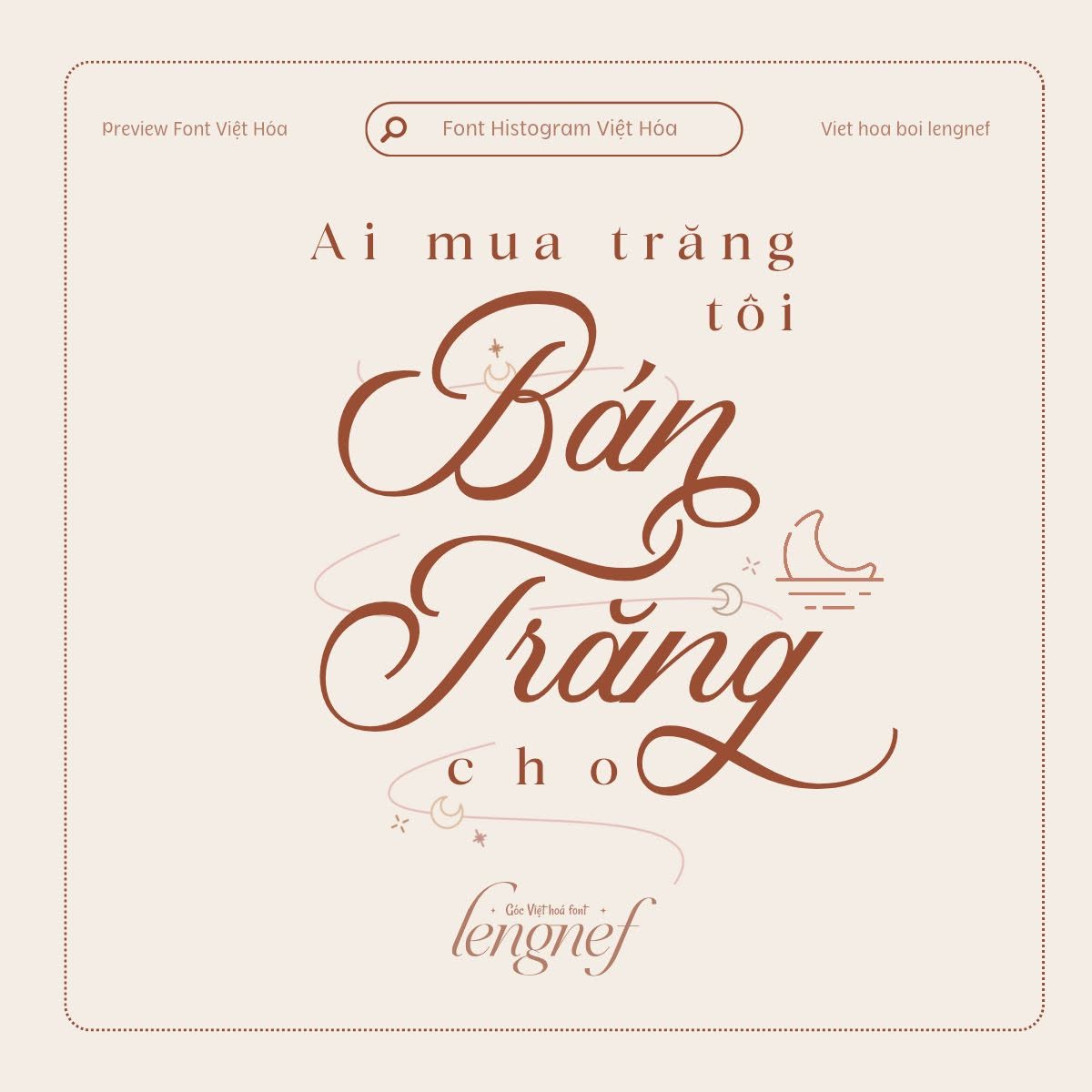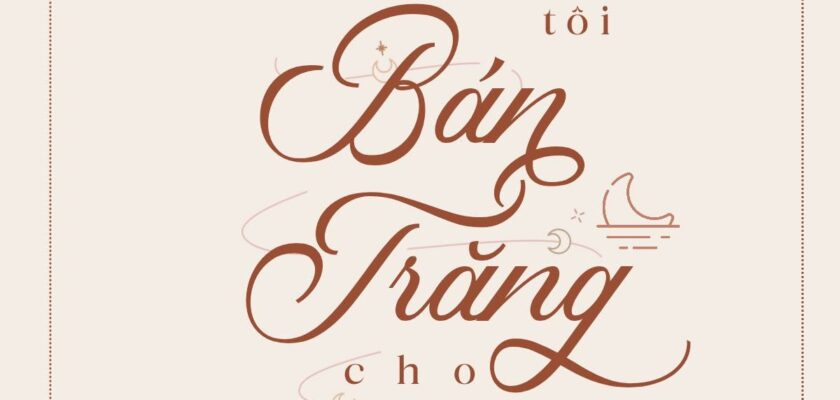
Share Font 70 || LF Histogram
- Tác giả: Arendxstudio
- Việt hóa: lengnef
Histogram là một phông chữ viết tay theo phong cách kết hợp giữa cổ điển và hiện đại, được lấy cảm hứng từ chữ viết tay cổ điển trong sách. Phông được thêm một số glyph uốn lượn có thể ứng dụng vào nhiều thiết kế như: thiệp mời, logo brand, tiêu đề, banner…